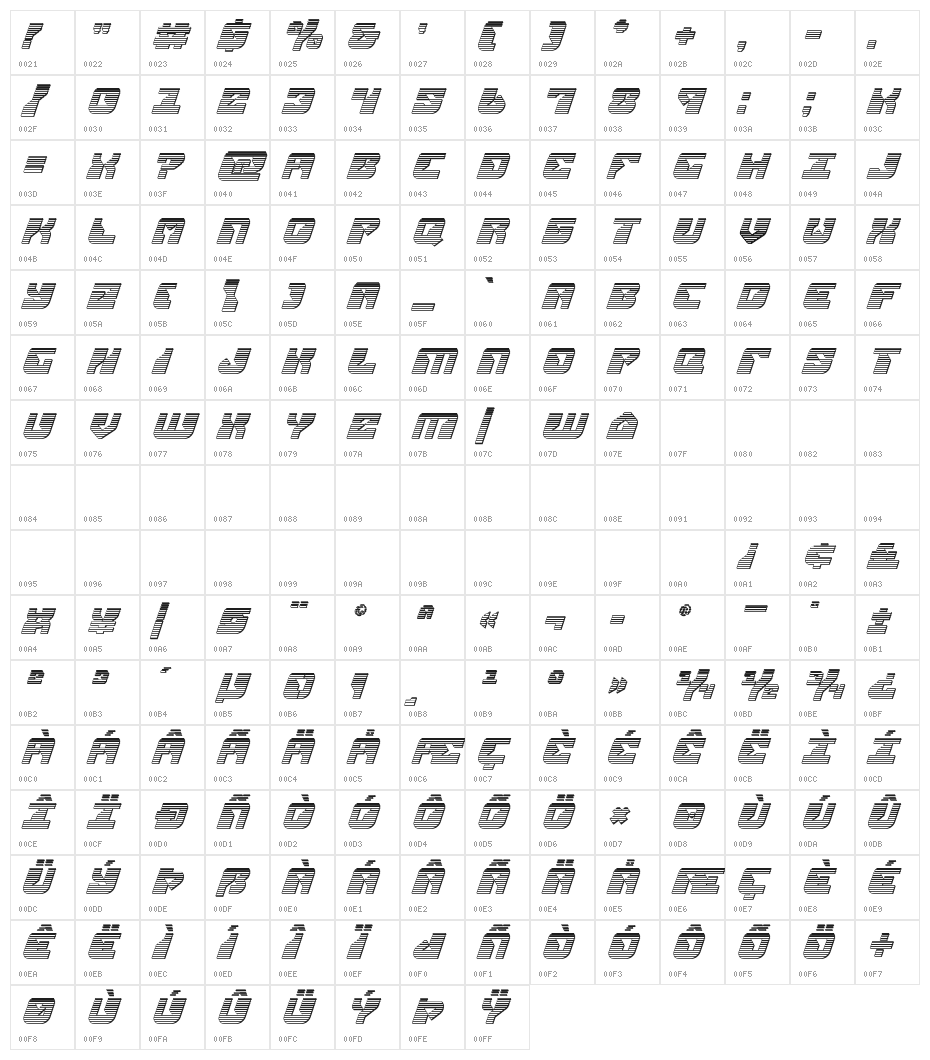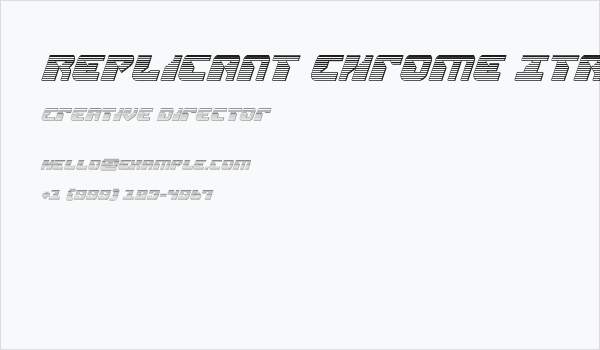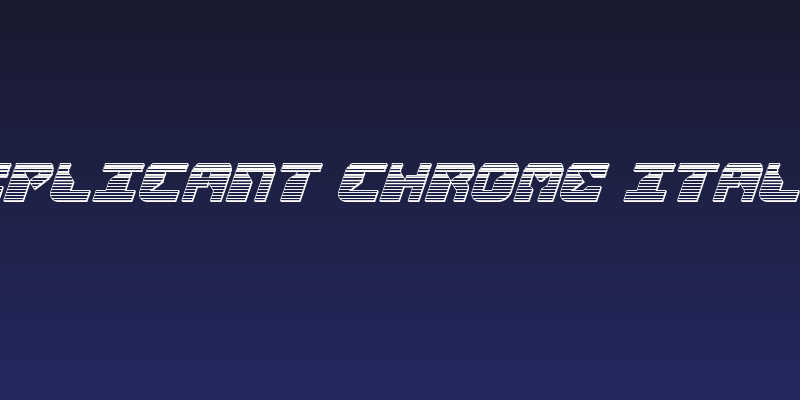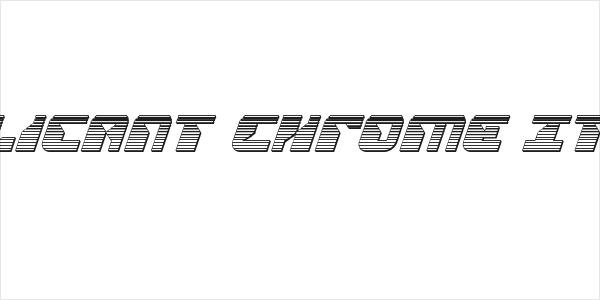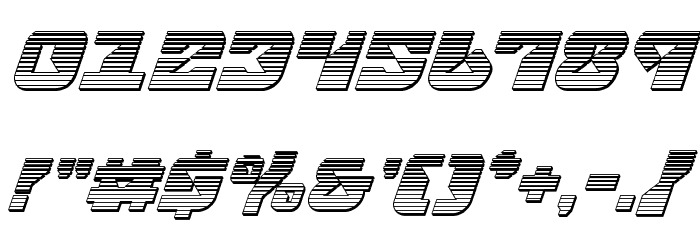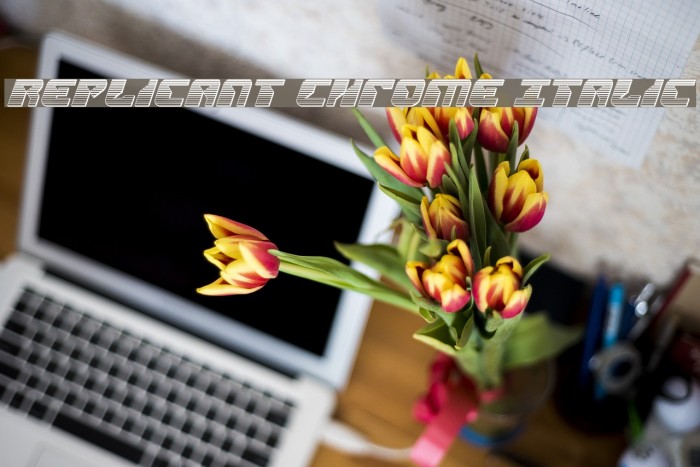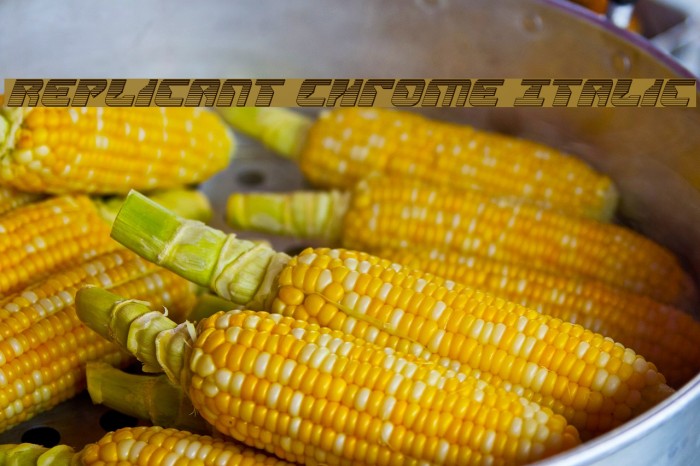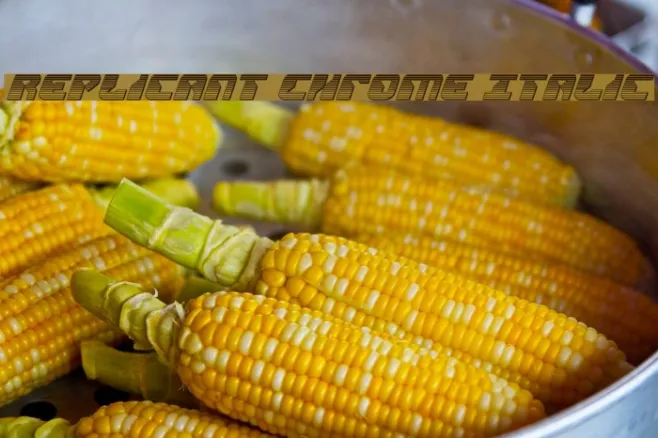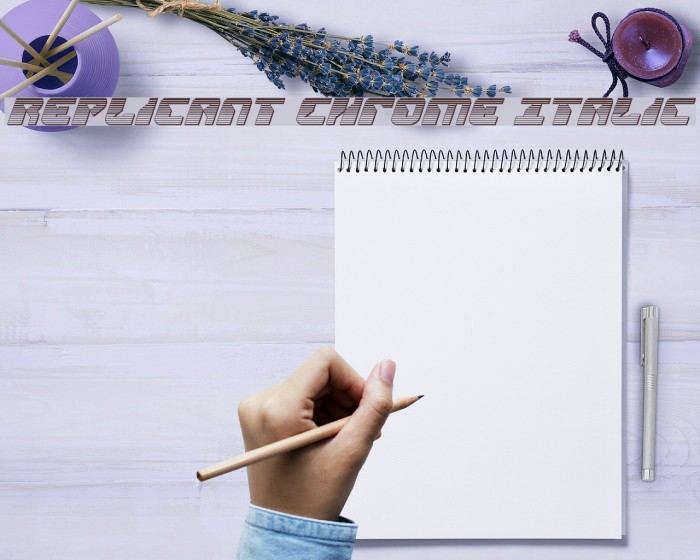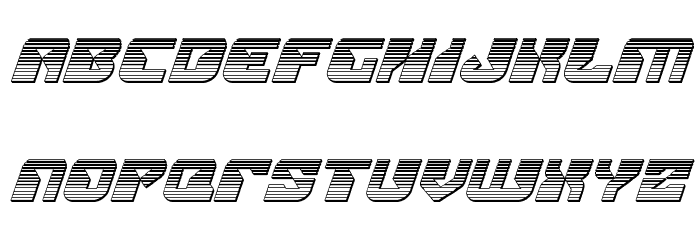
Replicant Chrome Italic Font
| Proyectos propuestos | Ideal for technology branding, sci-fi themed designs, video game titles, and futuristic posters. |